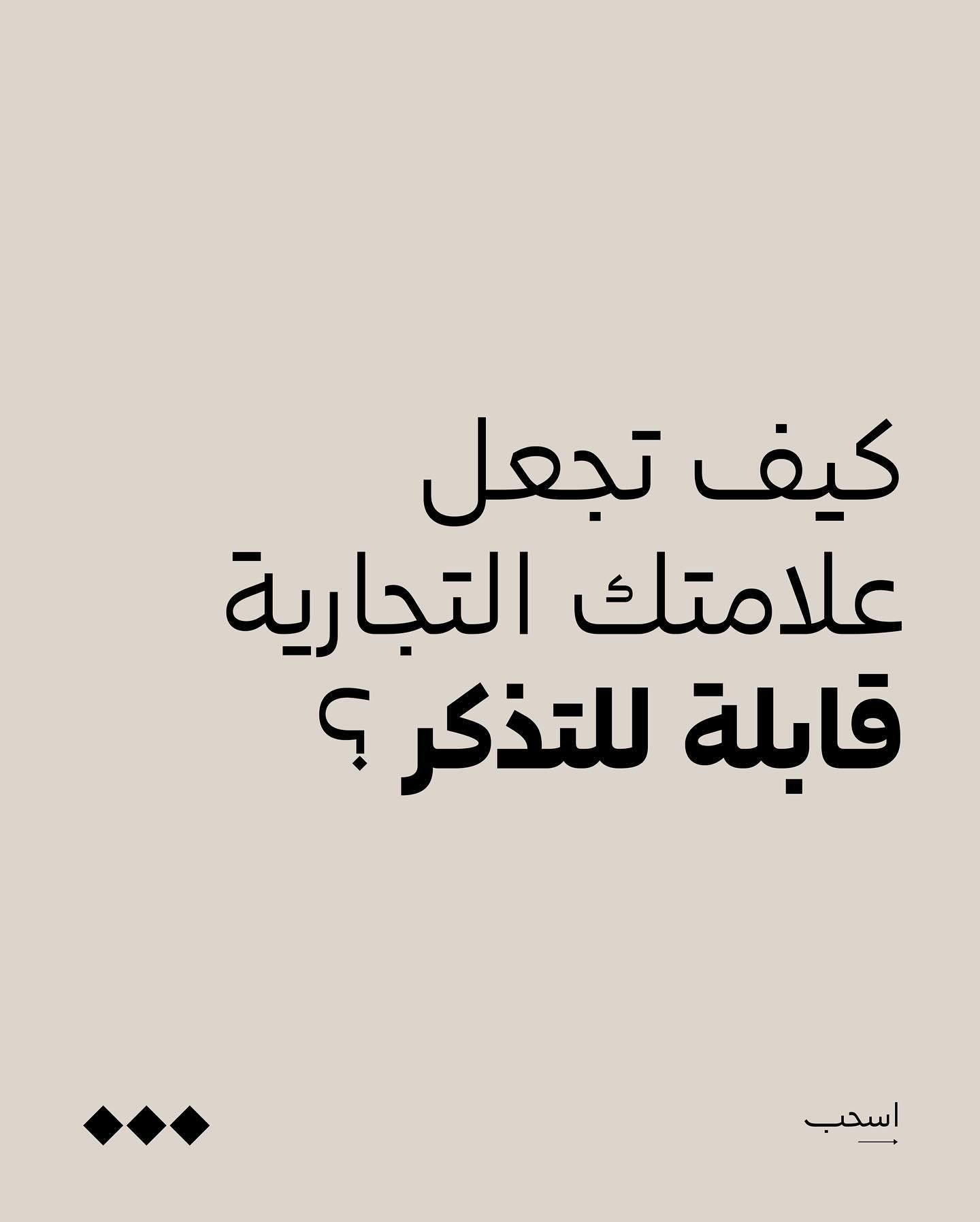
استخدام خط امينة نسخ -شغف Shaghf
أمنية نسخ هو خط عربي نسخ حديث واصدار من خط أمنية ويتميز بالأنحناءات الجمالية التي تعكس دقة التفاصيل . يجمع الخط بين الجمال والبساطة في تجربة كتابية فريدة وغنية بالتفاصيل .
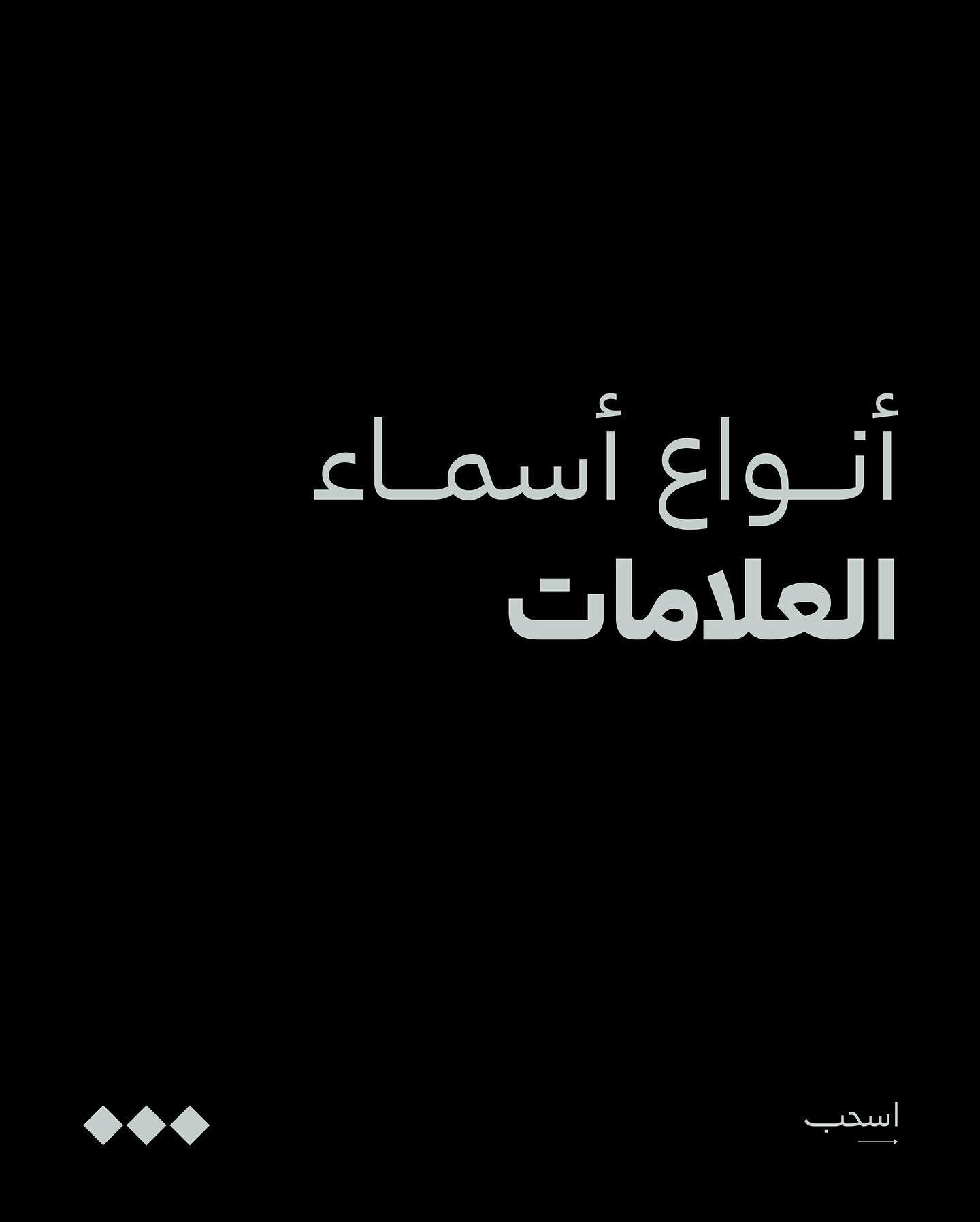
أمنية نسخ هو خط عربي نسخ حديث واصدار من خط أمنية ويتميز بالأنحناءات الجمالية التي تعكس دقة التفاصيل . يجمع الخط بين الجمال والبساطة في تجربة كتابية فريدة وغنية بالتفاصيل .